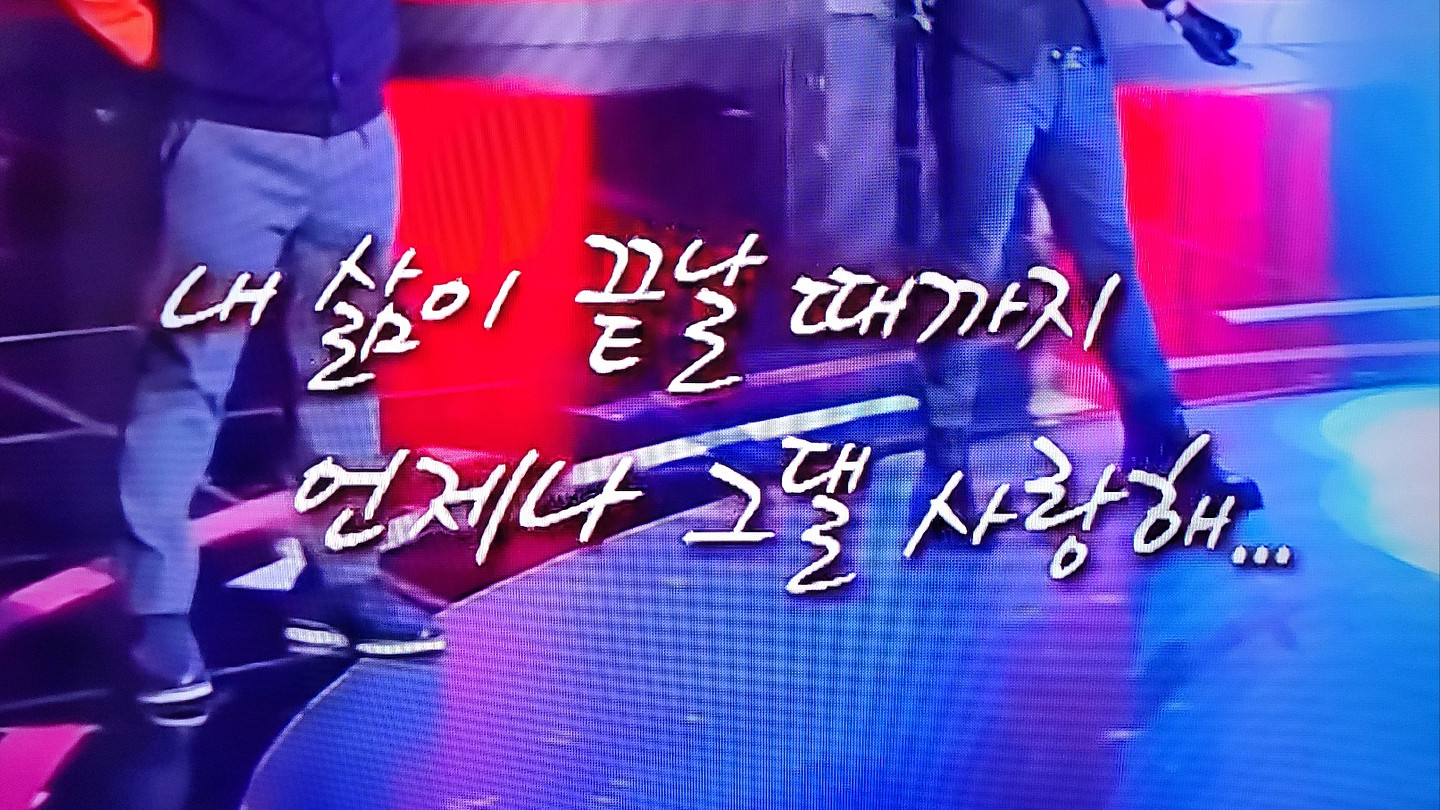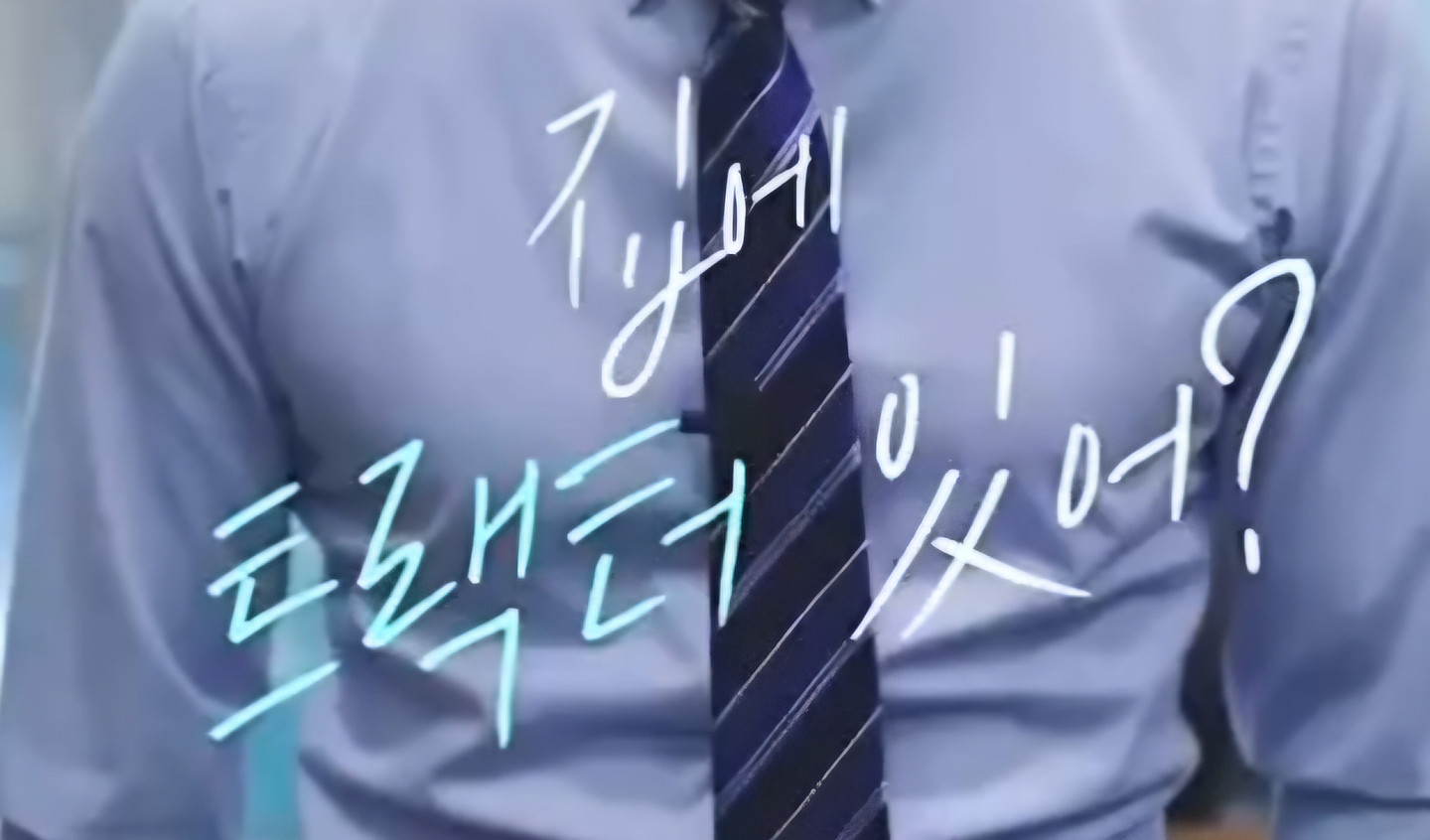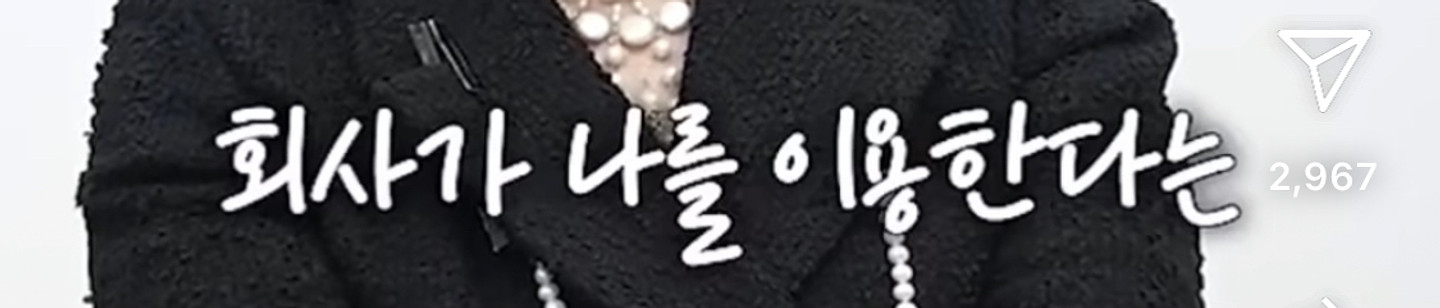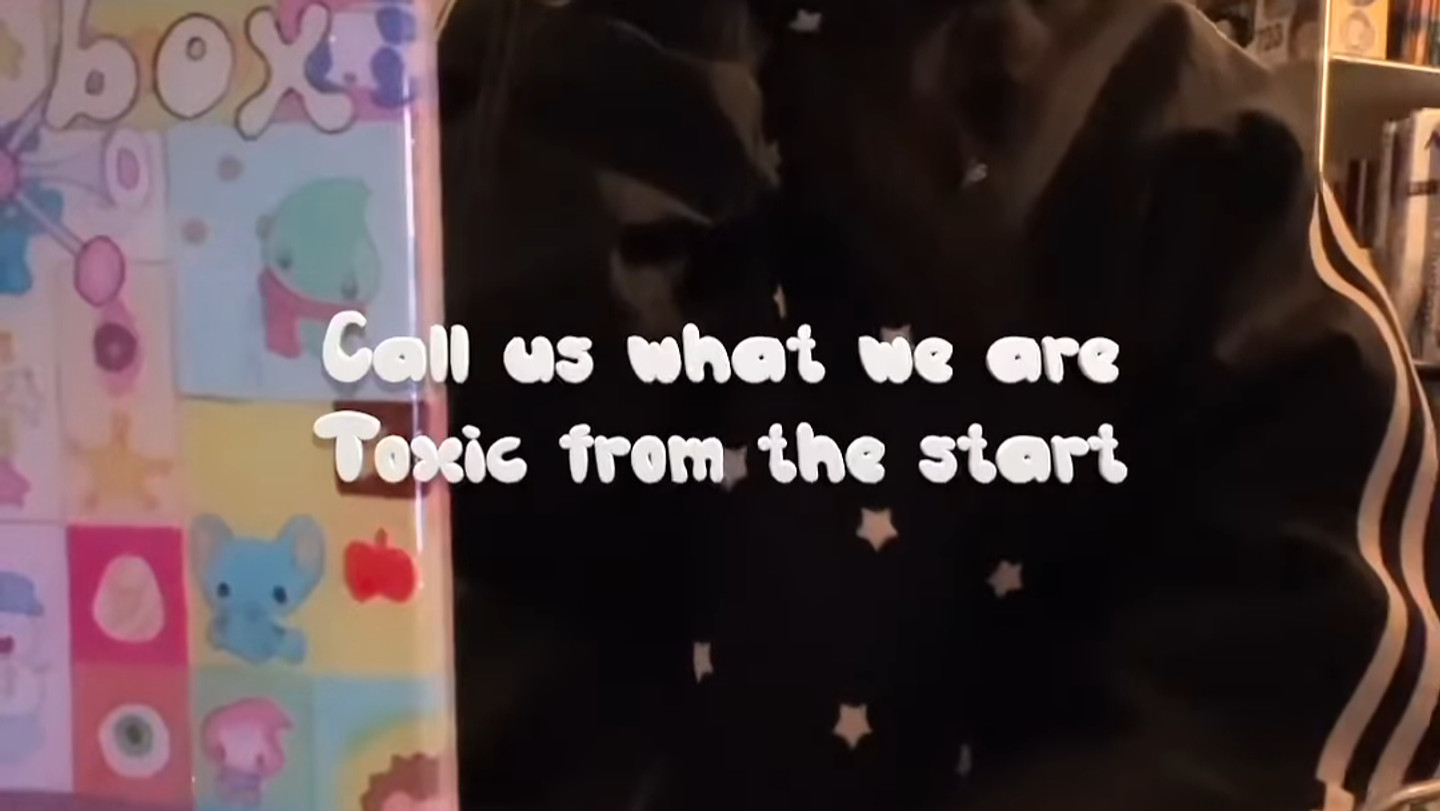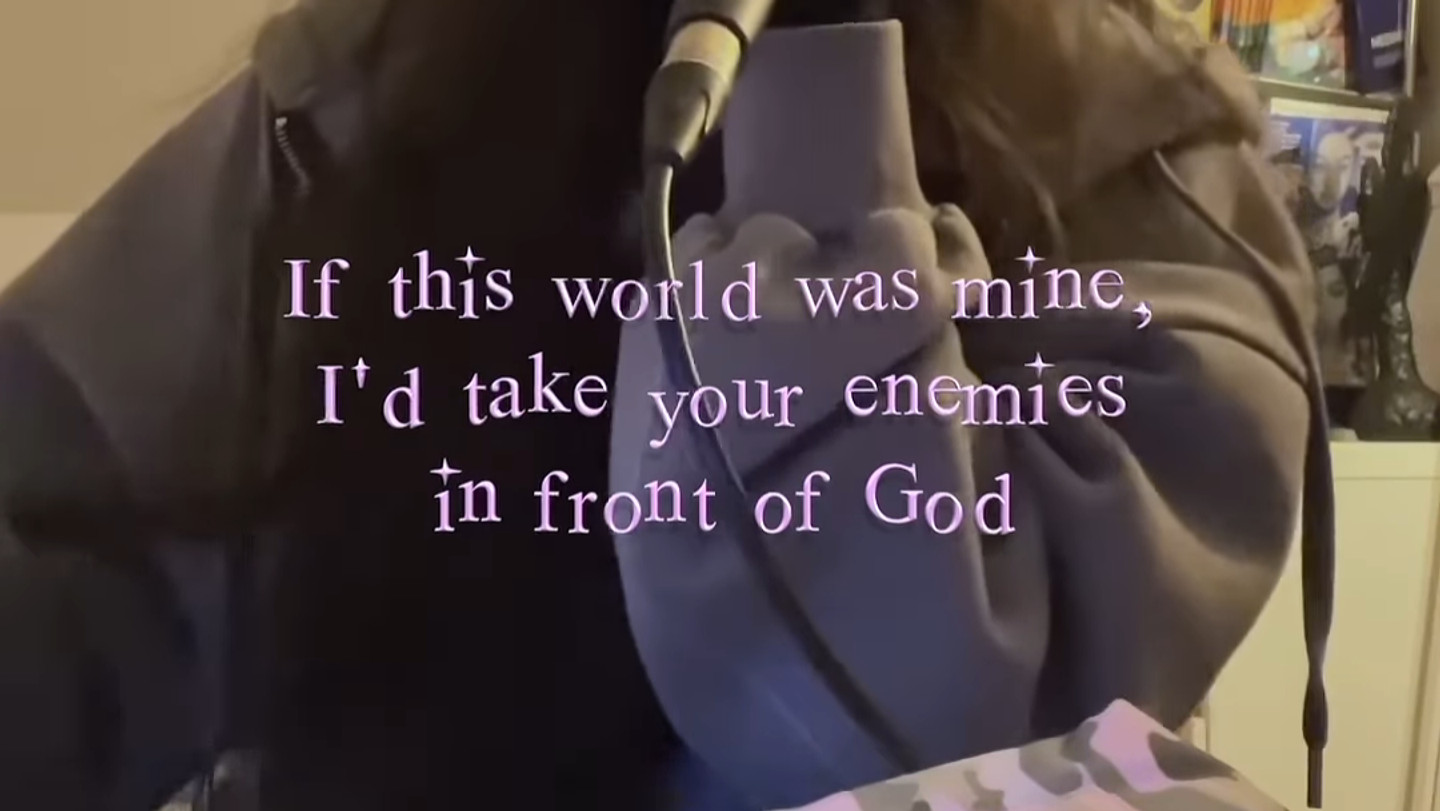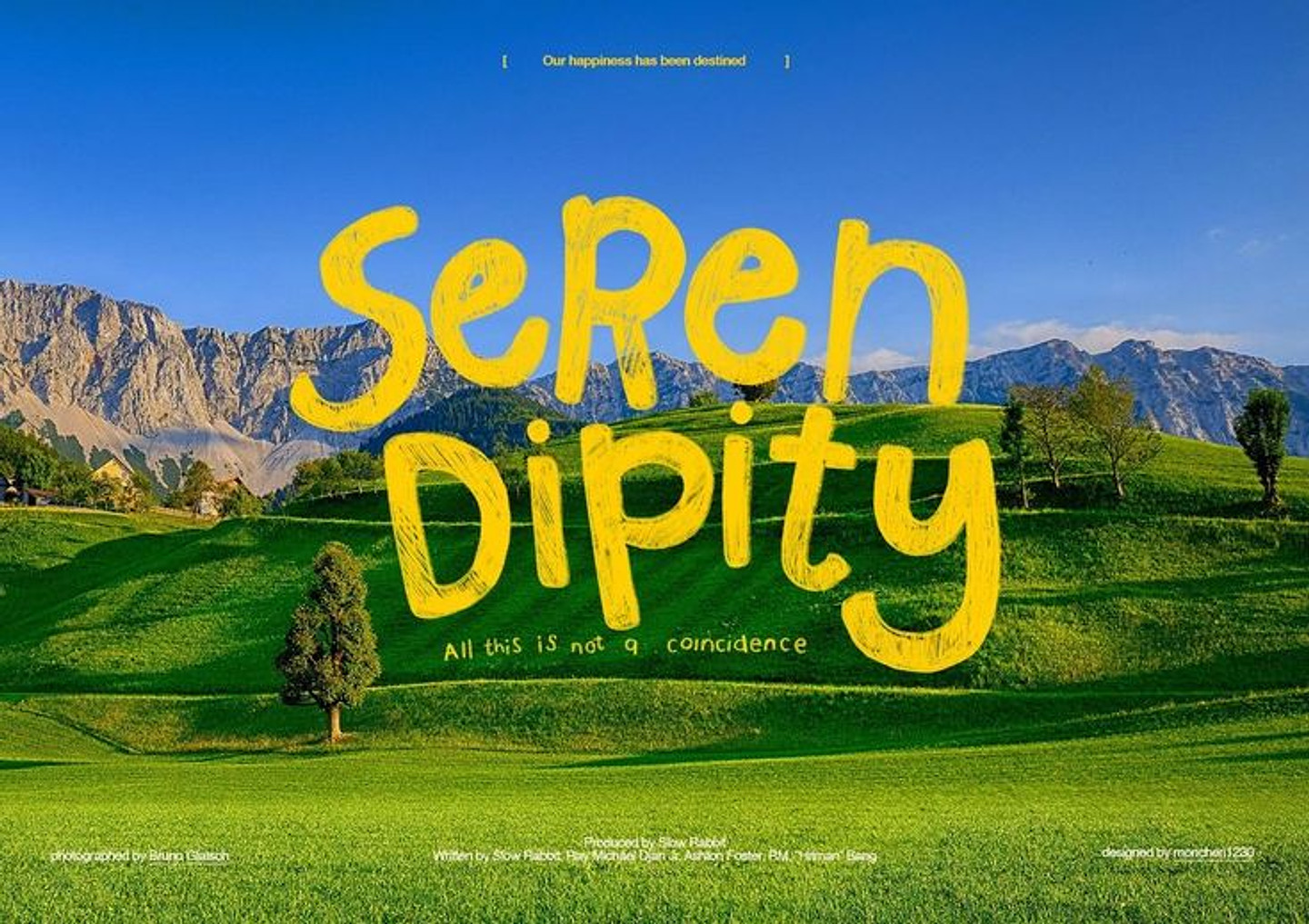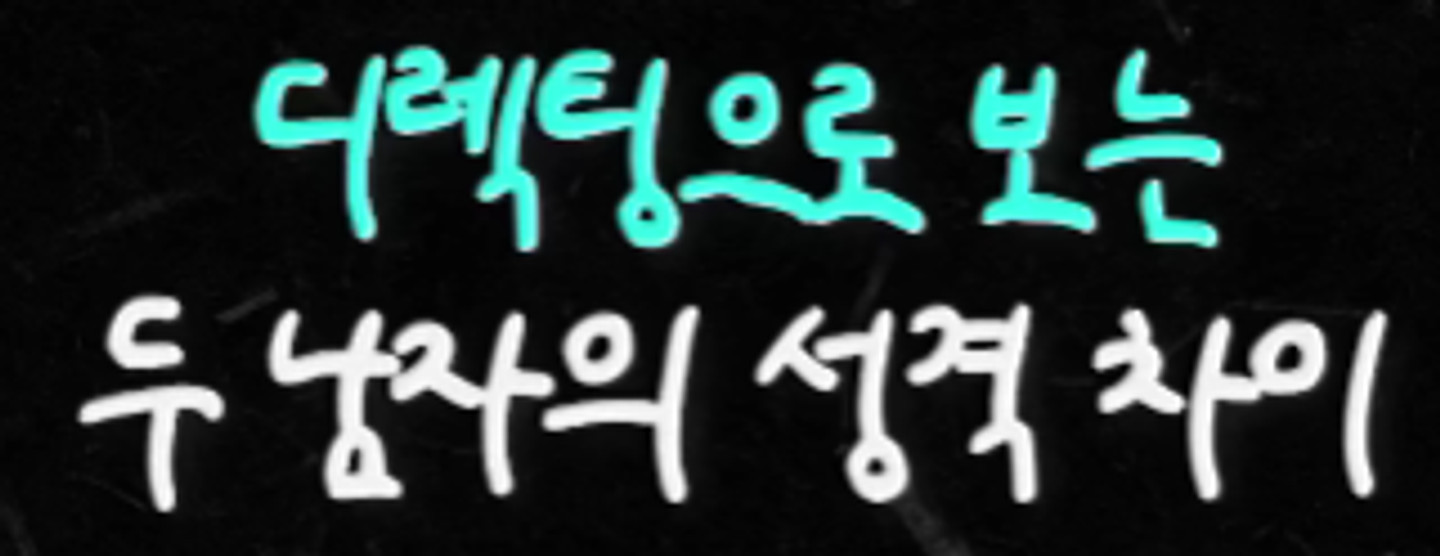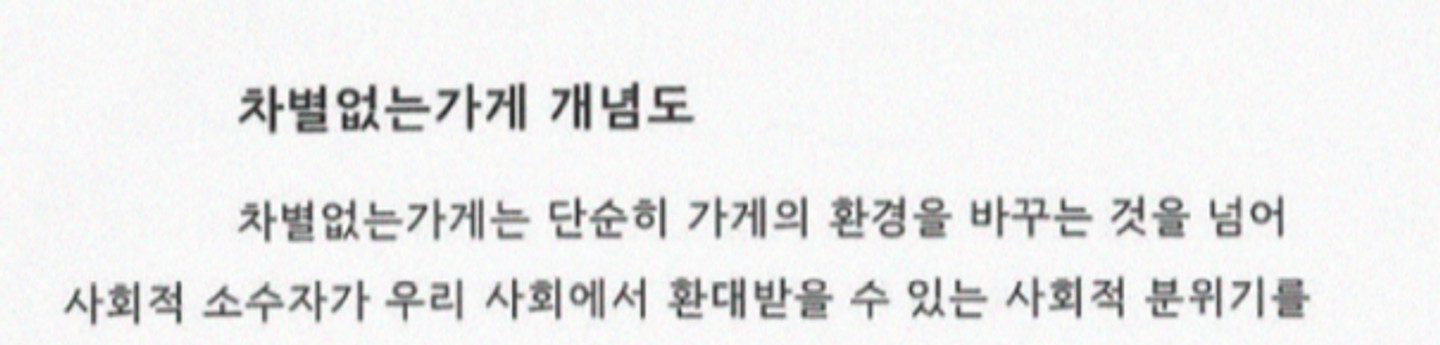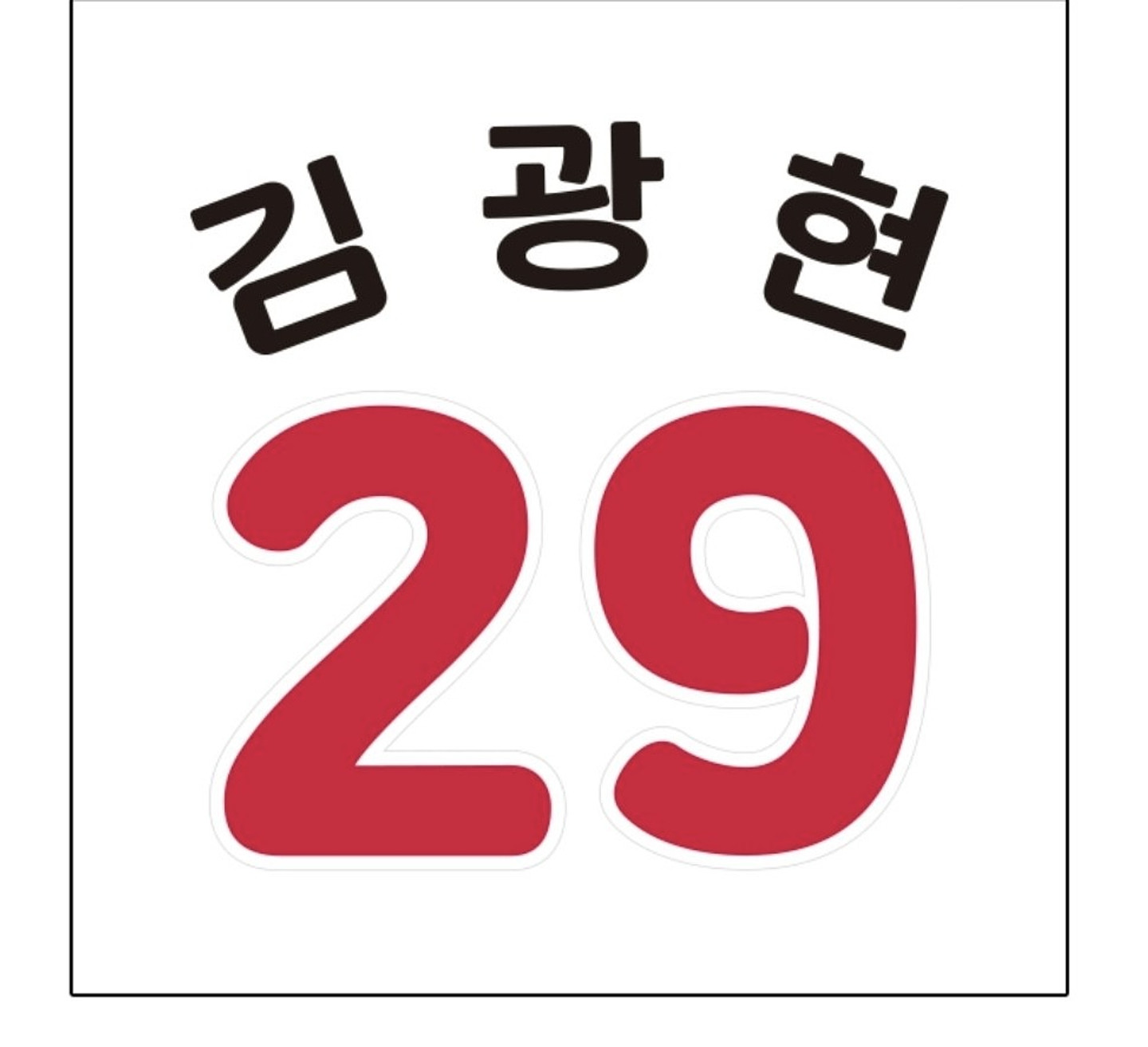
전에 어느 분이 올렸던 건데, 답변이 안 달려서 제가 다시 한 번 올려봅니다. 어떤 폰트일까요? 나름 찾아봤는데 경기체, 서울체는 아닌 거 같아요.. 정확한 폰트를 알고 싶습니다.
이 영상에 나온 폰트 무슨 폰트인가요?..ㅠㅠ 제발 알려주세요 https://youtu.be/3ERtNZqh1XA?si=A3zEwQqEyfbgoBpq
학교 시험지 폰트인데 정말 궁금합니다.. 제가 일일이 하나하나 대조해 본 결과 일단 신명조 계열은 아닌 것 같고요 영문 서체와 국문 서체가 같은 폰트인 것 같습니다. 폰트 고수님들 제발 부탁드립니다..!
오래 전(10년도 더 된 것 같아요 ㅠㅠ) 다운받아 카카오톡에서 사용하던 글씨체 인데.. 어떤 거였는지 까먹었네요 ㅠㅠ 아시는 분 알려주세요~
만화책에서 나온 폰트인데, 어떤 폰트인지 궁금합니다. 만화 이름은 주술회전이고, 출판사는 서울미디어코믹스입니다.
(주)삼우코리아 워드마크 폰트 정보좀 부탁드립니다. http://www.samudies.co.kr/korean/page/sub1_6.html